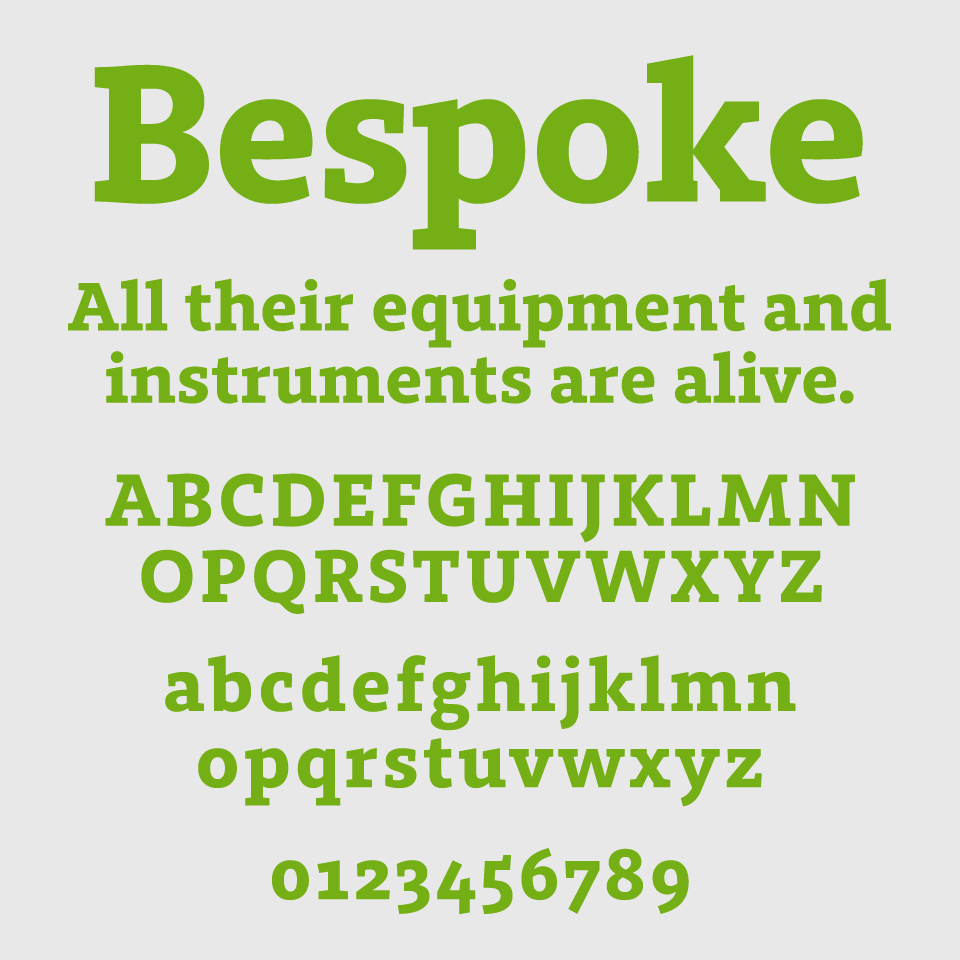
Bespoke Slabフォントは、どっしりと安定感のあるウェイトと、柔らかなカーブが特徴的なスラブセリフ体のフォントです。
角ばりすぎず、丸みも感じさせる造形により、力強さと親しみやすさが共存しています。特にaやe、gなどの小文字に見られる丸みが、全体の印象を優しく整えています。
文字の太さは程よく、視認性にも優れているため、見出しやタイトル用途にも適しています。ウェイトも10スタイルと幅広く揃っています。
| 作者 | Fontshare |